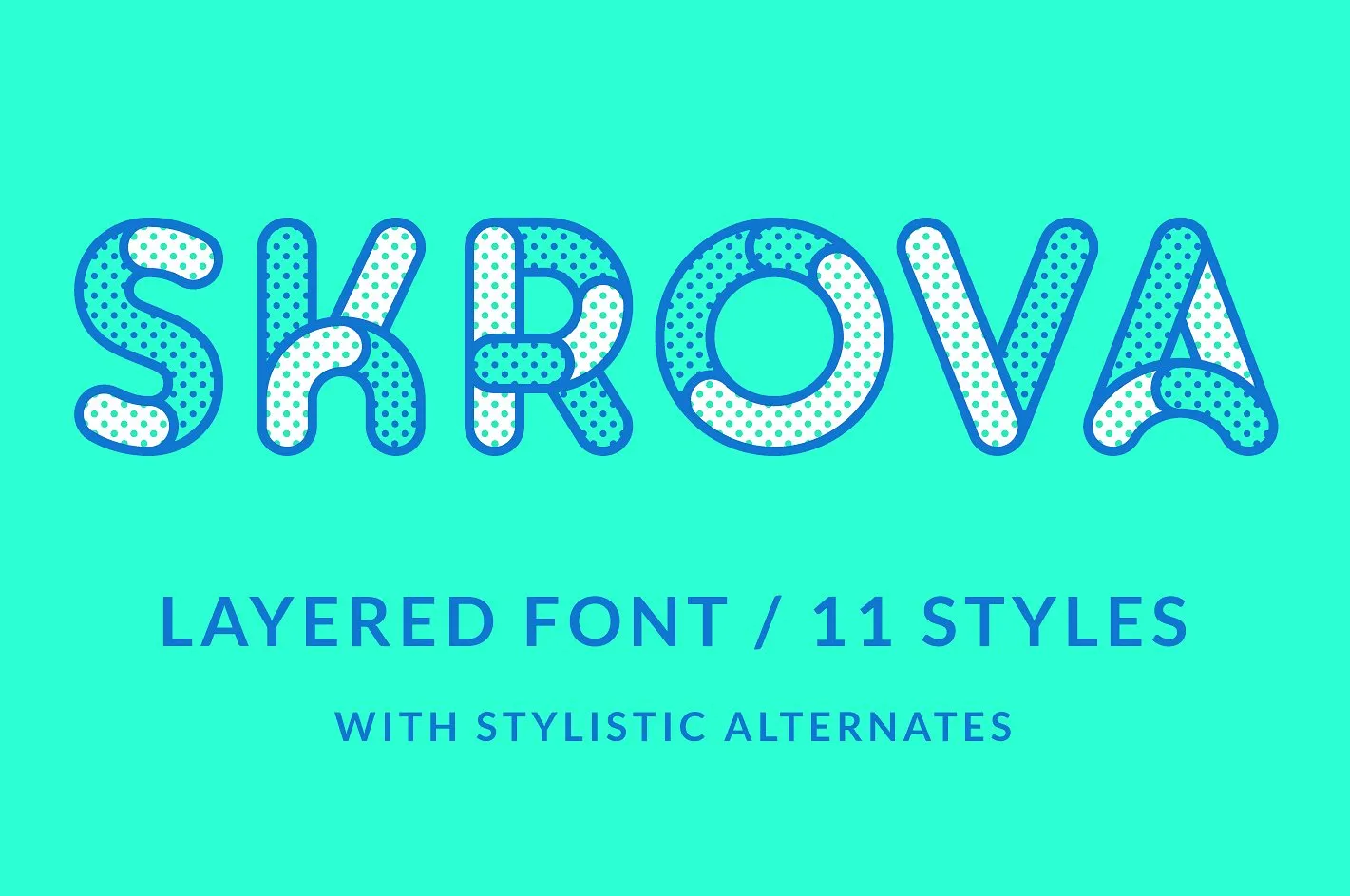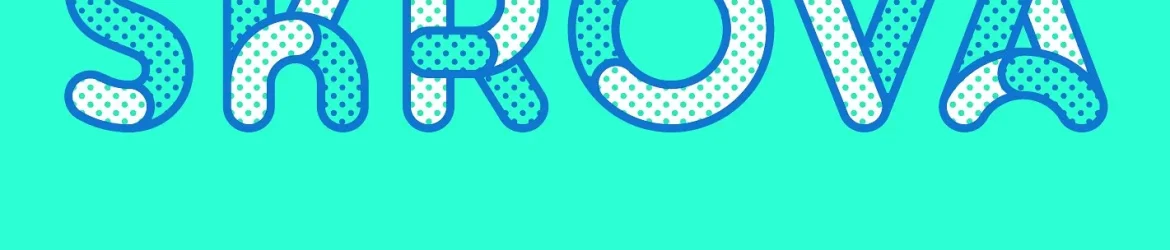
Skrova Layered Font – Download Grátis
Introduzimos a Skrova Layered Font! Desenvolvida pelo Studio Dot by dot, essa fonte é uma mistura de estilos que traz 11 personalizações distintas para seu uso criativo. Esta seleção elegante inclui todos os marcadores de pontuação da Europa Ocidental e alternativas estilísticas, tornando-a perfeita para quem busca um toque de modernidade em seus projetos. Com um único caso, ou unicase como é chamado, você pode adicionar uma dimensão única a qualquer design – com todas as letras em maiúsculas ou minúsculas. Seja para o seu próximo projeto editorial, marca de desporto ou até mesmo para dar um toque especial aos designs gráficos do dia a dia, a Skrova Layered é definitivamente uma fonte que merece ser explorada.